Звёздочка-сноска в рукописном шрифте: как нарисовать знак *
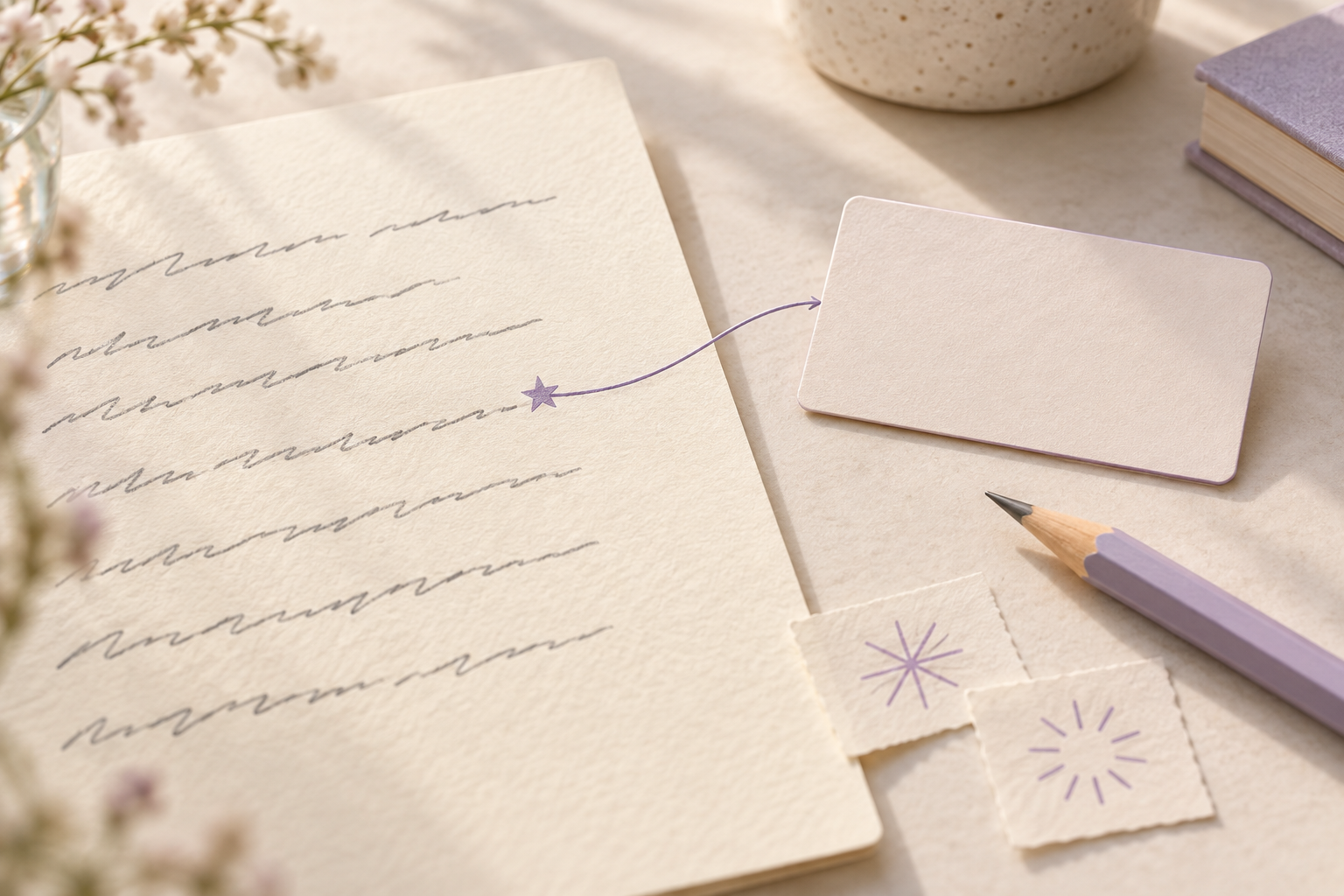
Звёздочка-сноска в рукописном шрифте должна быстро находиться рядом с текстом и не превращаться в декоративную звезду. Для этого задайте ей отдельный характер, соразмерьте высоту с верхним регистром и проверьте в реальной строке: после слова, рядом с цифрой и над ссылкой на примечание. Ниже — практический порядок рисунка и проверки знака * U+002A.
Сначала определите роль знака
Одна и та же форма звёздочки может выглядеть как пунктуация, украшение или математический оператор. Если читатель встречает её после слова «Состав*», он должен понять, что рядом есть примечание; если знак стоит в орнаменте или на обложке, он может быть декоративным. Поэтому до рисования решите, где именно будет работать ваш глиф: в основном наборе текста, в кратких подписях, в меню или в справочном материале.
Знак U+002A ASTERISK в таблице Unicode показан как отдельный символ; в описании указано, что у него может быть пять или шесть лучей. В той же таблице приведены отдельные похожие знаки, например низкая звёздочка и оператор астериск. Это помогает не смешивать разные кодовые позиции, если набор действительно должен поддерживать их все. Для обычной текстовой сноски начните с самого символа *, а декоративный знак заведите отдельно только при реальной потребности. Свериться с названиями и кодами можно в списке Unicode для Basic Latin.
Составьте короткую карту применений. Например: основной знак * ставится после слова и ссылается на пояснение под текстом; декоративная звезда появляется только в заголовке; знак умножения относится к математическому набору. Если пока нужен лишь один вариант, не пытайтесь одним рисунком идеально обслужить все роли. Такая карта предотвращает случайное копирование орнаментальной формы в мелкий набор.
Как нарисовать звёздочку, которая читается в строке
Начните с силуэта, который узнаётся в небольшом размере. У астериска важен не блеск и не ощущение эмблемы, а компактный центр и несколько чётких направлений. В рукописном стиле не обязательно делать лучи абсолютно одинаковыми: лёгкая неровность сохраняет характер почерка. Но разница между ними должна быть намеренной и повторяемой, иначе знак распадается на случайную кляксу.
Сделайте быстрый эскиз из пяти или шести лучей и сравните его с самой простой геометрической версией. При пяти лучах удобнее сохранить свободные промежутки и не перегрузить центр. Шесть лучей могут лучше поддержать плотный, симметричный алфавит, но легко слипнуться при уменьшении. Это не правило Unicode и не обязательная норма дизайна: выберите тот вариант, который сочетается с характером букв и остаётся различимым на ваших пробах.
Уточните центр пересечения. Слишком тонкие штрихи теряются на грубой бумаге или в маленьком кегле; слишком толстые создают тяжёлое пятно. Нарисуйте знак тем же инструментом и с тем же нажимом, что и основные буквы. Если линии в шрифте слегка расширяются к концу, повторите это свойство умеренно. Не утолщайте все лучи автоматически: у рукописной звёздочки могут быть разные направления и порядок штрихов, но пятно в центре должно оставаться собранным.
Проверьте наклон. В прямом начертании вертикальный луч часто даёт устойчивую ось; в наклонном рукописном наборе знак может иметь общий наклон или сохранять почти симметричный рисунок. Сравните оба решения рядом с прописными и цифрами. Если глиф заметно «падает» в одну сторону, знак будет казаться случайной помаркой. Если он слишком правильный и чужой почерку, попробуйте изменить форму концов лучей, а не ломать всю симметрию.
Размер и положение маркера
Для сноски знак обычно ставят после слова или фрагмента, к которому относится пояснение. В конкретной публикации правила пробелов и надстрочного набора зависят от редакционного стандарта и макета. Ваша задача при разработке глифа — предусмотреть, что его могут поднять относительно строки или уменьшить средствами набора. Проверьте его и в обычной строке, и в предполагаемом формате надстрочного маркера; не исходите из того, что один размер будет одинаково хорошо работать во всех вариантах.
Сравните высоту звёздочки с цифрой верхнего регистра и строчными выносными элементами. Если она слишком крупная, маркер перетягивает внимание; если крошечная, теряется после слова. Для теста поставьте знак после коротких и длинных слов, после заглавной буквы и после цифры: «Состав*», «важно*», «5*». В каждом примере посмотрите не только на форму, но и на соседний пробел. Иногда знак кажется неудачным из-за слишком тесного или слишком широкого интервала, хотя сам рисунок удачен.
Боковые поля должны позволять поставить знак после буквы без столкновения луча с соседним контуром. Но большой боковой пробел тоже опасен: звёздочка начинает выглядеть отдельным значком. Сравните интервалы в нескольких сочетаниях, например «текст*», «слово *» и «5*». Не копируйте механически одно значение для всех знаков: у наклонных рукописных букв могут быть выступающие части, а у астериска — лучи, заходящие в боковые поля. Оцените результат на целой строке, а не только в изолированной таблице.